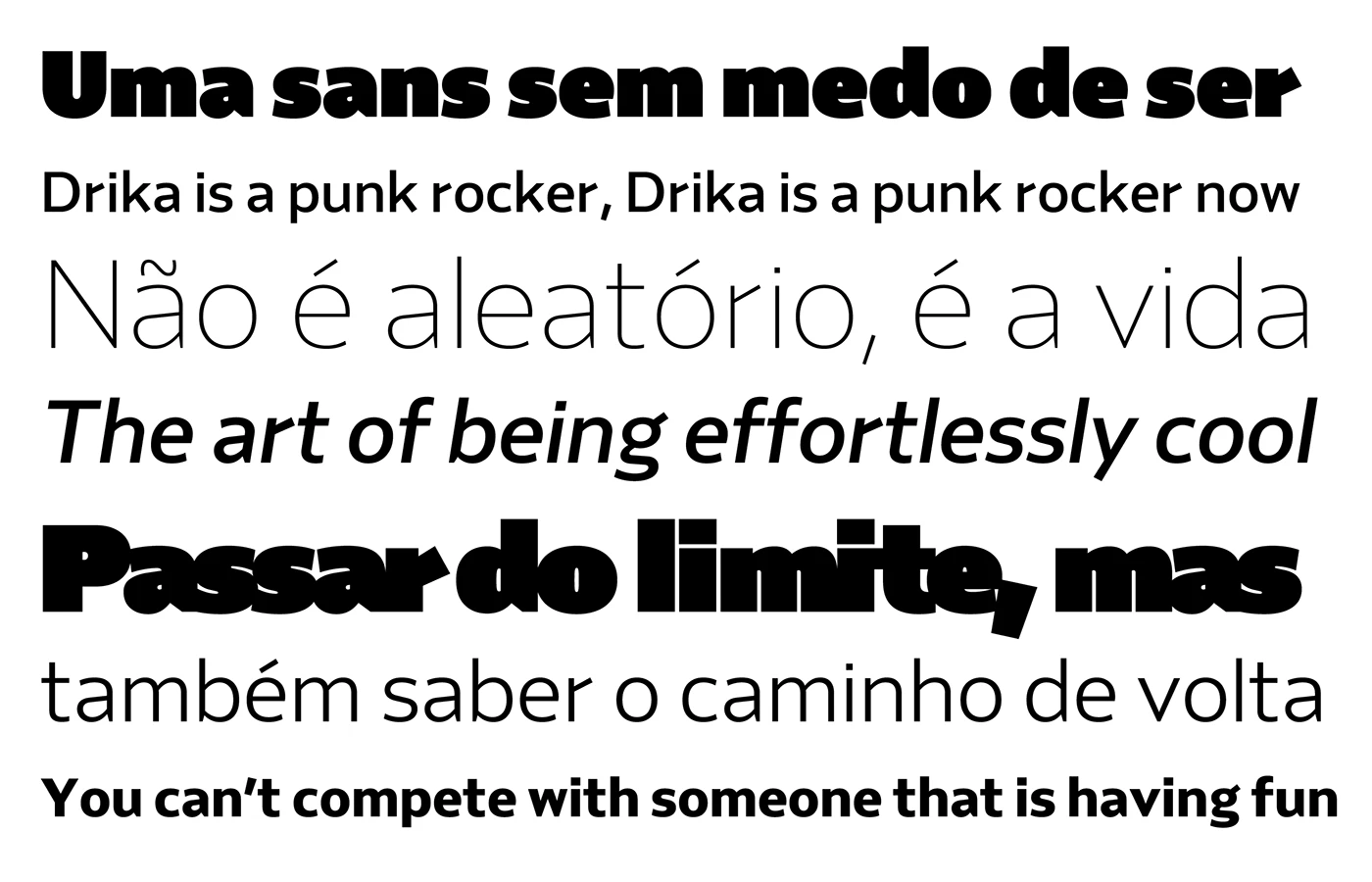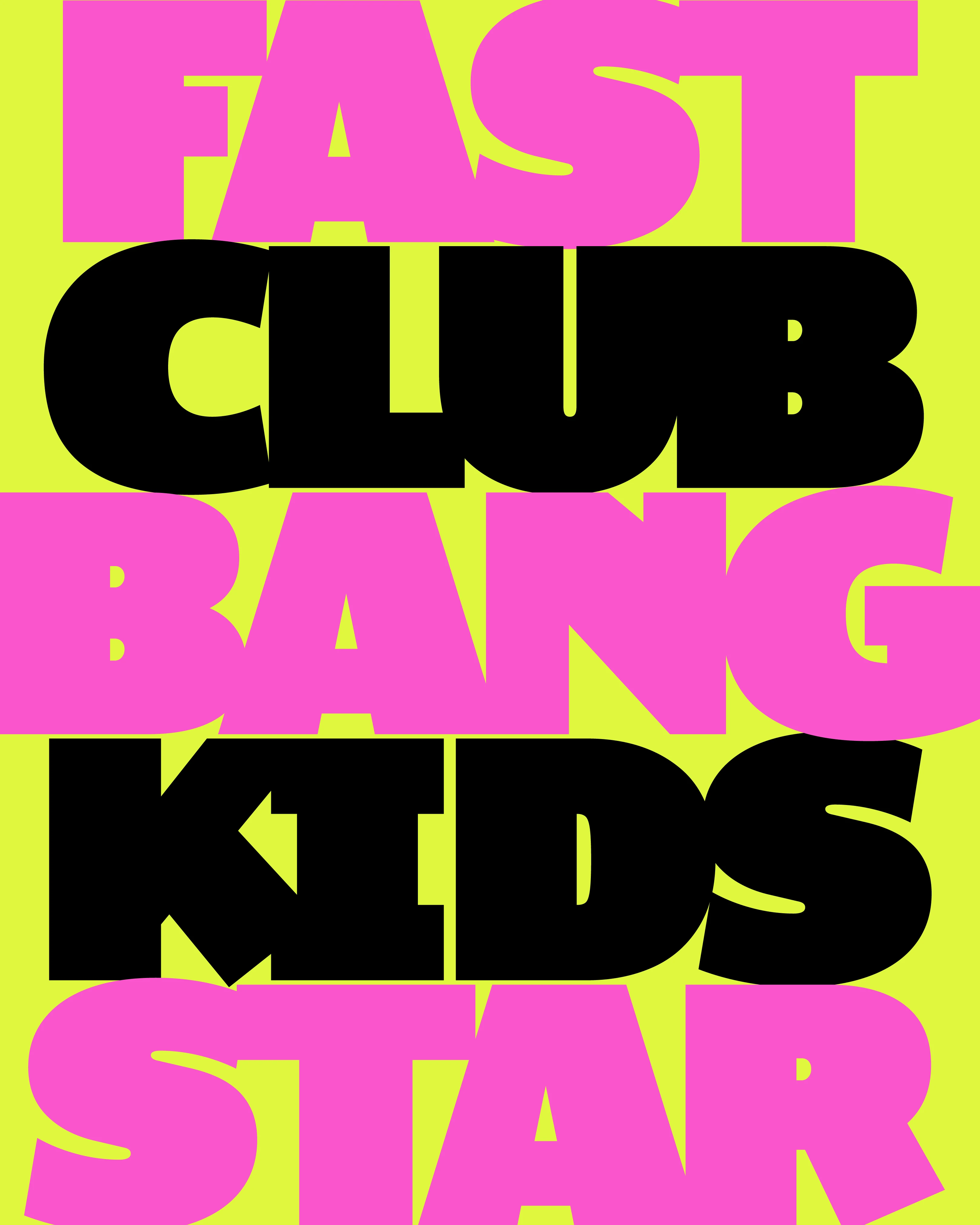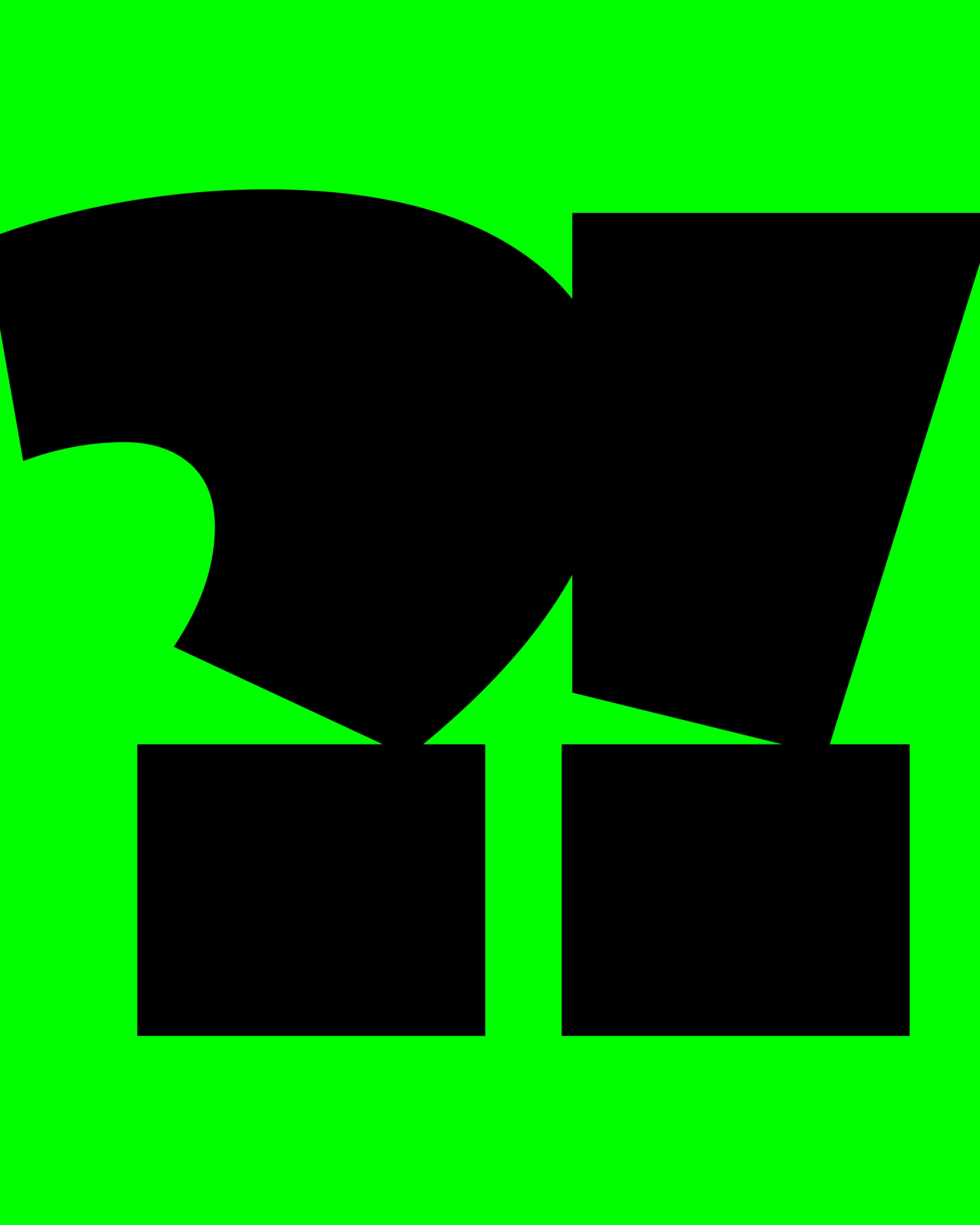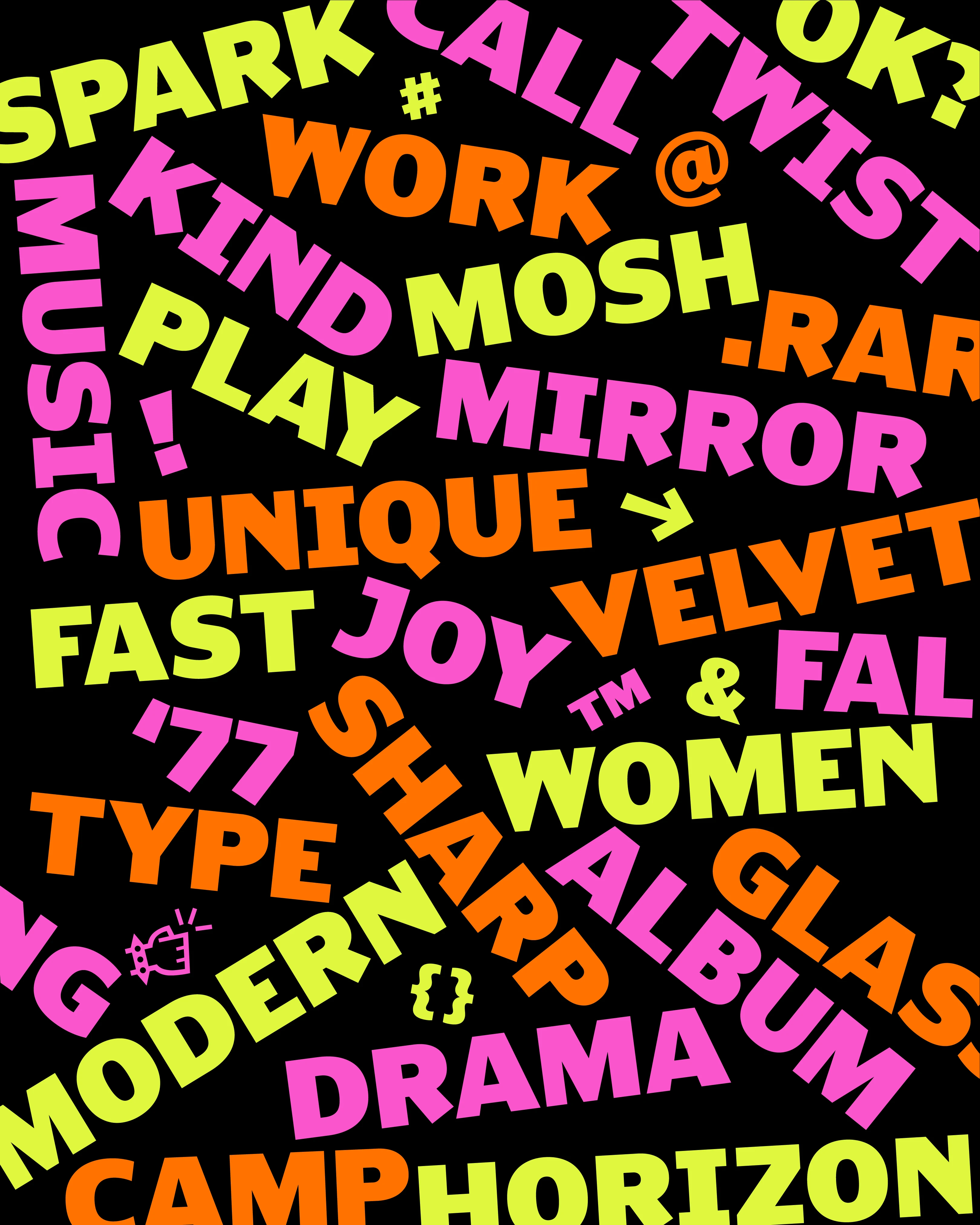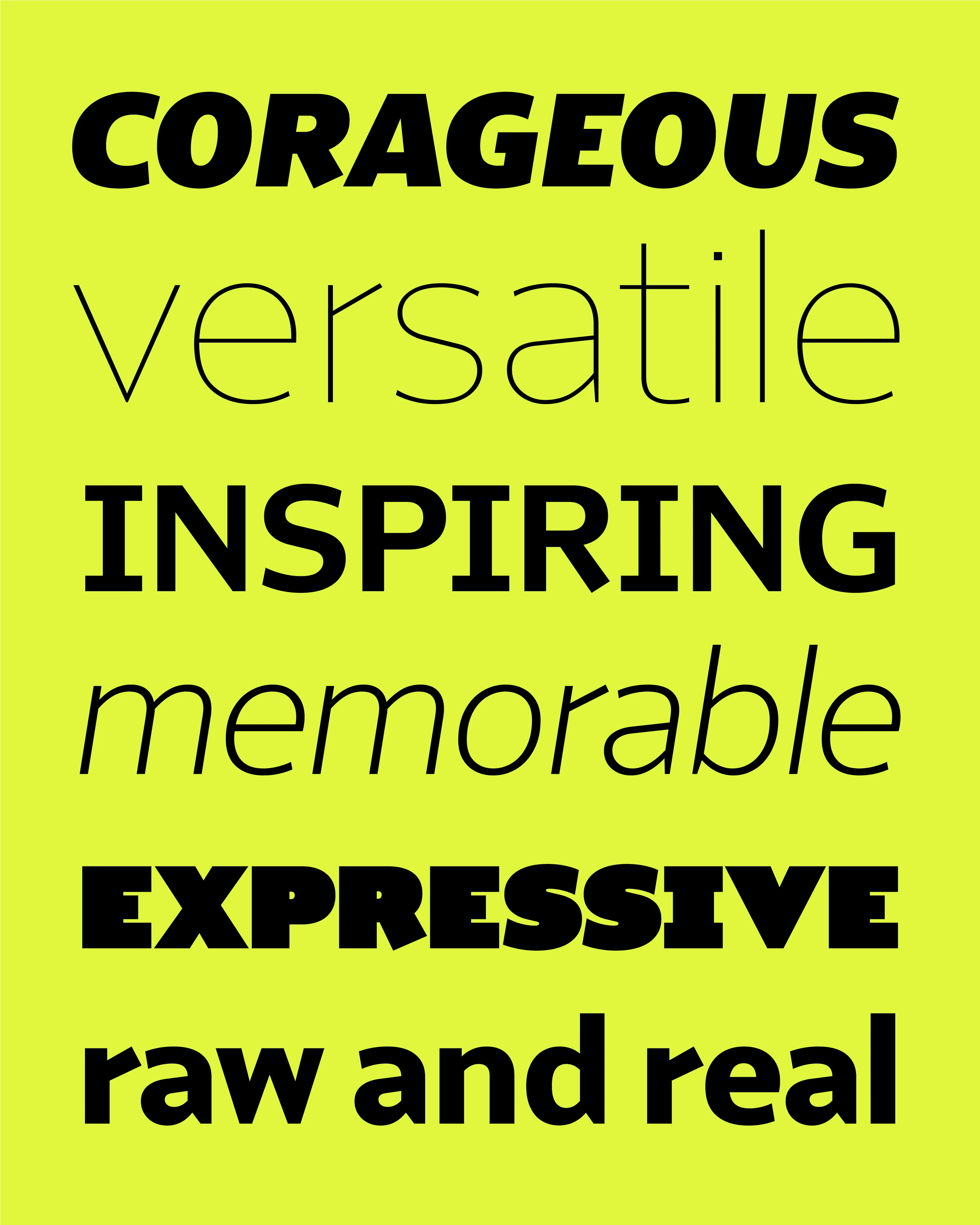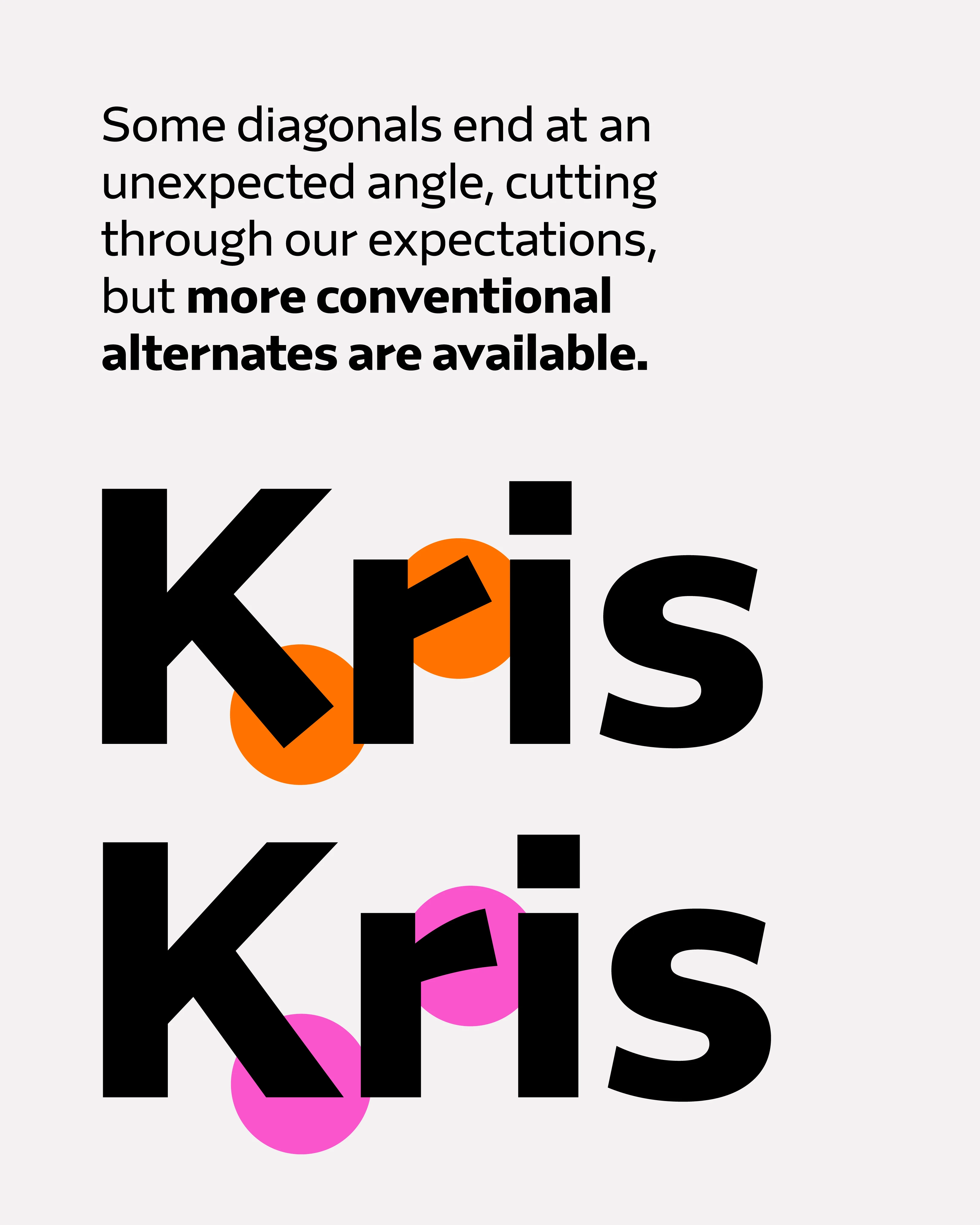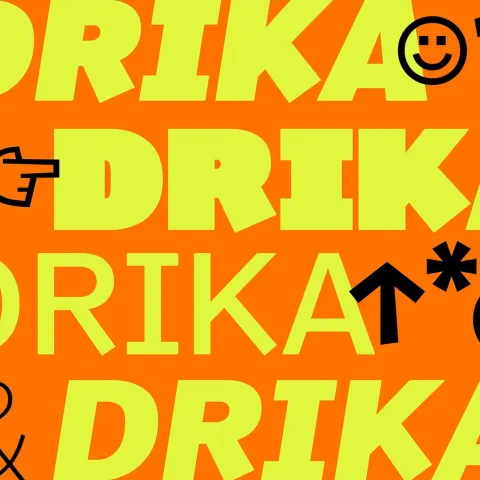
Cái tên Drika với chữ “k” đầy kiêu hãnh đã phần nào nói lên cá tính riêng biệt của bộ font này. Được nhà thiết kế https://www.behance.net/gallery/251023713/Drika-a-sans-unafraid-of-being nhào nặn với 14 định dạng (weights) khác nhau, Drika mang đến một dải sắc thái cực rộng: từ những nét Hairline thanh mảnh như những khoảng hở tinh tế, cho đến Extra-bold đậm đặc, chiếm trọn thị giác ngay từ cái nhìn đầu tiên.
Điểm đặc biệt nhất của bộ chữ chính là cách các ký tự tương tác với nhau. Thay vì giữ khoảng cách an toàn, chúng chọn cách “va chạm” – khi thì chỉ là một cái chạm nhẹ ở mép chữ, lúc lại lấn át mạnh mẽ vào không gian của nhau. Ở những định dạng mảnh nhất, sự chồng lấp này tạo cảm giác gần gũi, như hai chữ cái đang tựa vào nhau mà không làm mất đi hình dáng nguyên bản. Còn ở định dạng đậm, đó là những cú va chạm trực diện và đầy uy lực. Dù ở thái cực nào, cấu trúc của bộ chữ vẫn giữ được sự thống nhất mà không bị biến dạng.
Drika hiện đã gia nhập thư viện độc quyền của Fabio Haag Type, nơi hội tụ những bộ font được tuyển chọn kỹ lưỡng nhất từ Brazil. Không đơn thuần là một sản phẩm mang tính trang trí, Drika được thiết kế để xử lý tốt mọi bài toán thực tế: từ những dòng chú thích nhỏ trong dàn trang (editorial design) cho đến những tiêu đề khổ lớn. Với vẻ ngoài thô mộc, chân thực và không ngại phô diễn những điểm giao thoa sắc sảo, bộ font này là lựa chọn tuyệt vời cho các thiết kế nhận diện thương hiệu hay biên tập khi sự “trung tính” quá mức trở nên mờ nhạt. Set ở kích thước lớn, nó làm chủ hoàn toàn không gian; khi thu nhỏ, nó vẫn giữ vững phong thái mà không cần phải gồng mình.
Đây là một bộ Sans-serif đậm chất Brazil với khả năng tùy biến linh hoạt cho mọi nhu cầu thiết kế từ poster, branding đến các hệ thống thương hiệu phức tạp. Những hình thái chồng lấp không phải là ngẫu nhiên, mà là câu trả lời cho cách một bộ chữ thể hiện sức mạnh khi cần thiết. Với 14 lựa chọn độ dày, mọi cung bậc cảm xúc từ lời thì thầm nhẹ nhàng đến tiếng hét đầy quyền năng đều được hiệu chỉnh một cách chính xác nhất.